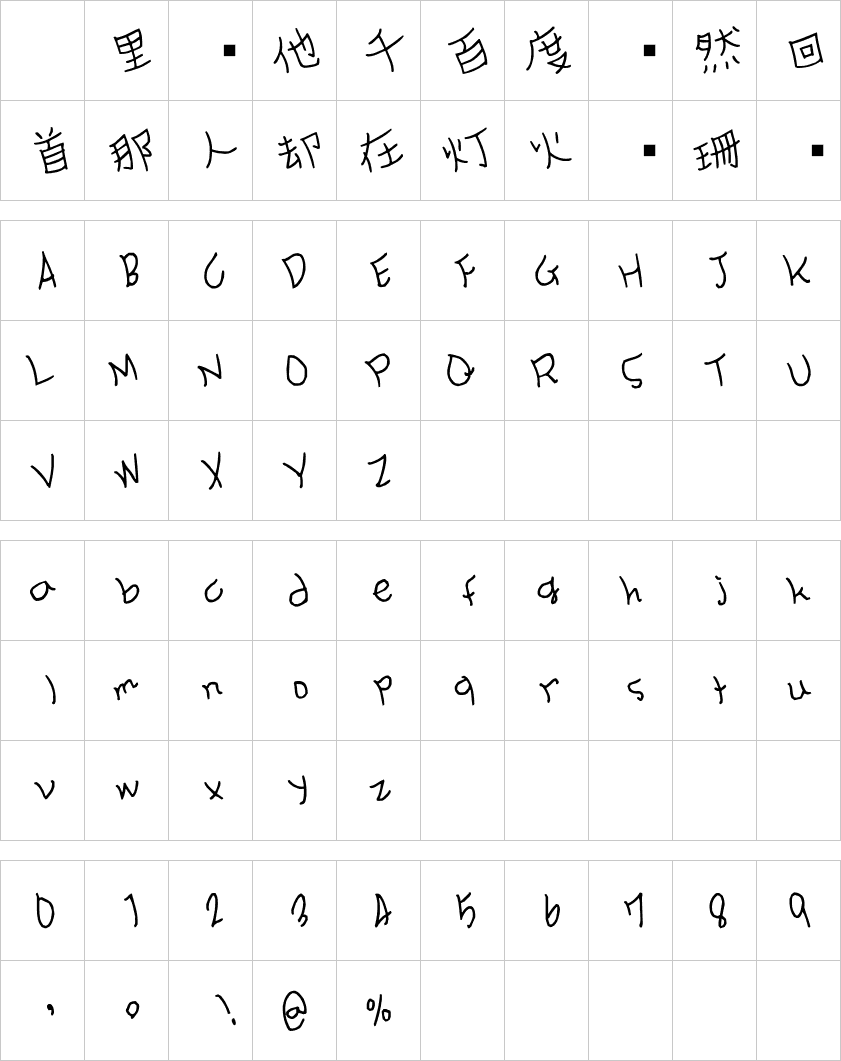
おひさまフォント
<説明>
・現役女子高生っぽく装ってみた、実用性のない手書きフォント。
・日本語2バイトかな文字フォント。等幅。一応縦書き対応。
・入ってる文字は、
ひらがな/全角・半角カタカナ/全角・半角数字/
全角・半角アルファベット/ギリシャ文字(小文字だけ)/
各種記号/絵文字/シフトJIS第一水準漢字/
シフトJIS第二水準漢字の、わりと使いそうな字を適当にチョイス
漢字も結構揃えたので、地名人名の他に困ることはあんまりないはず。